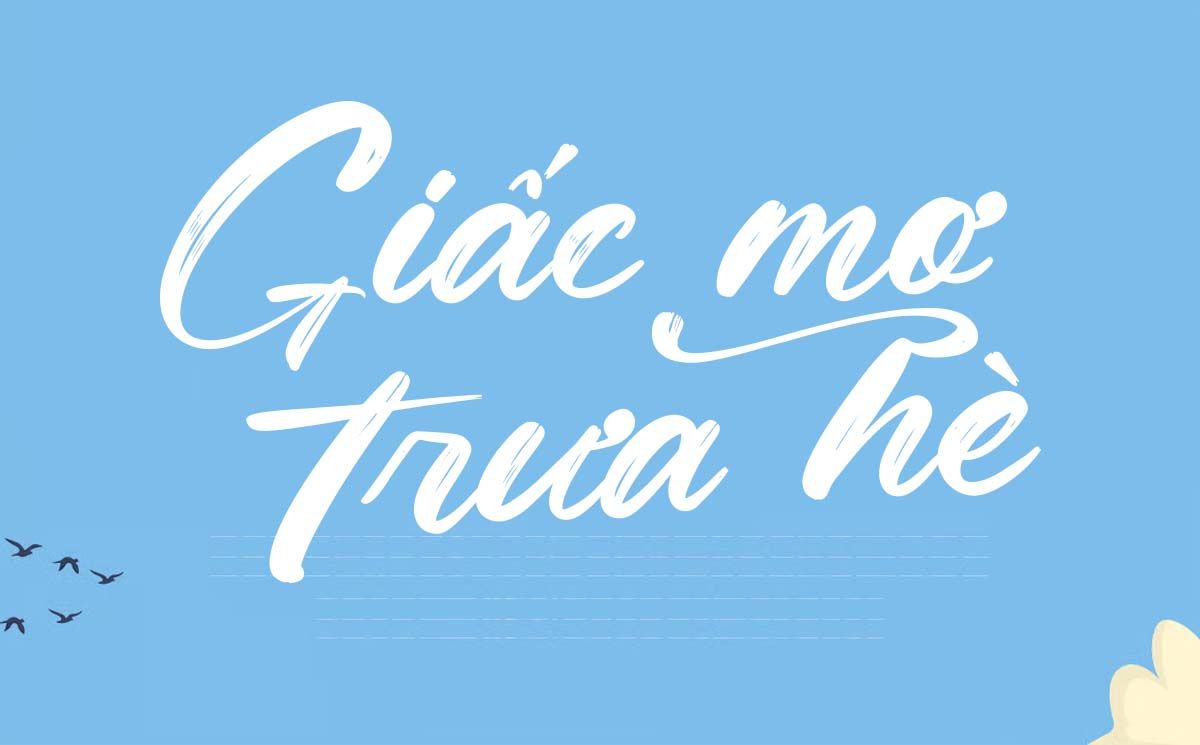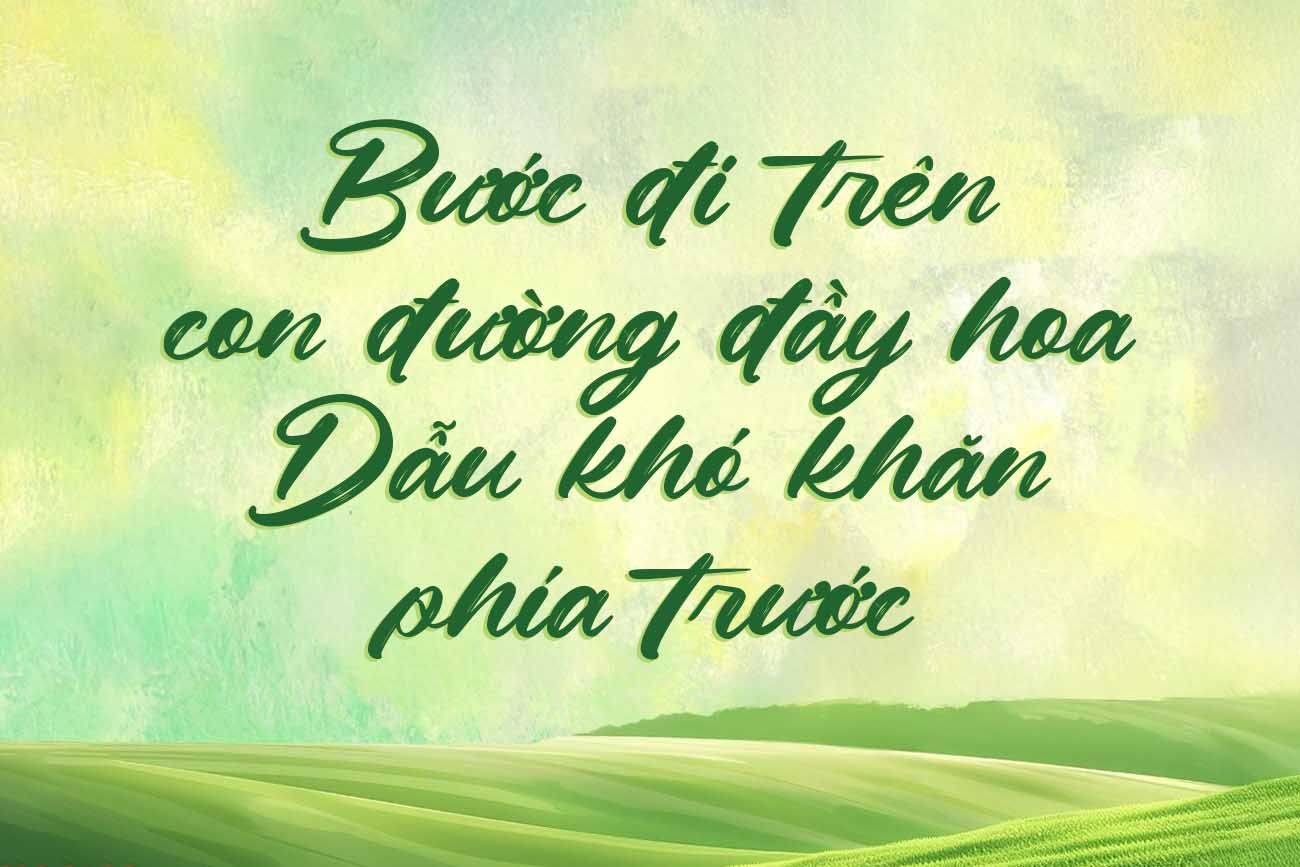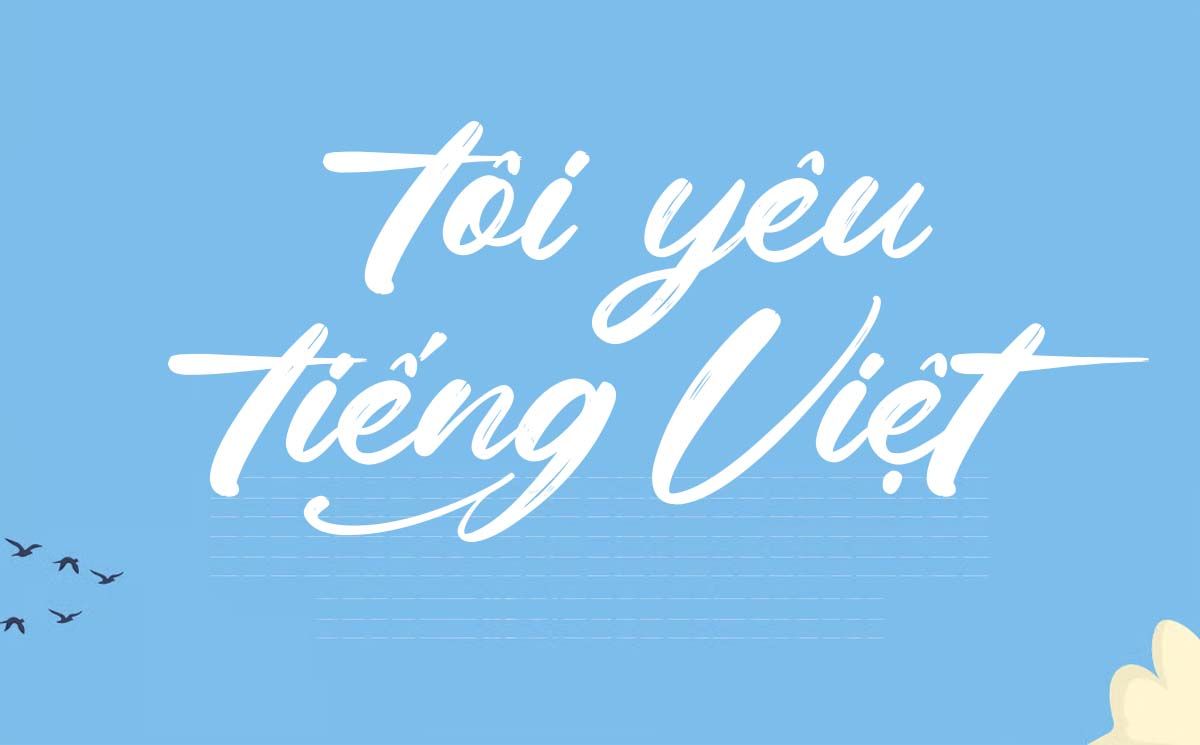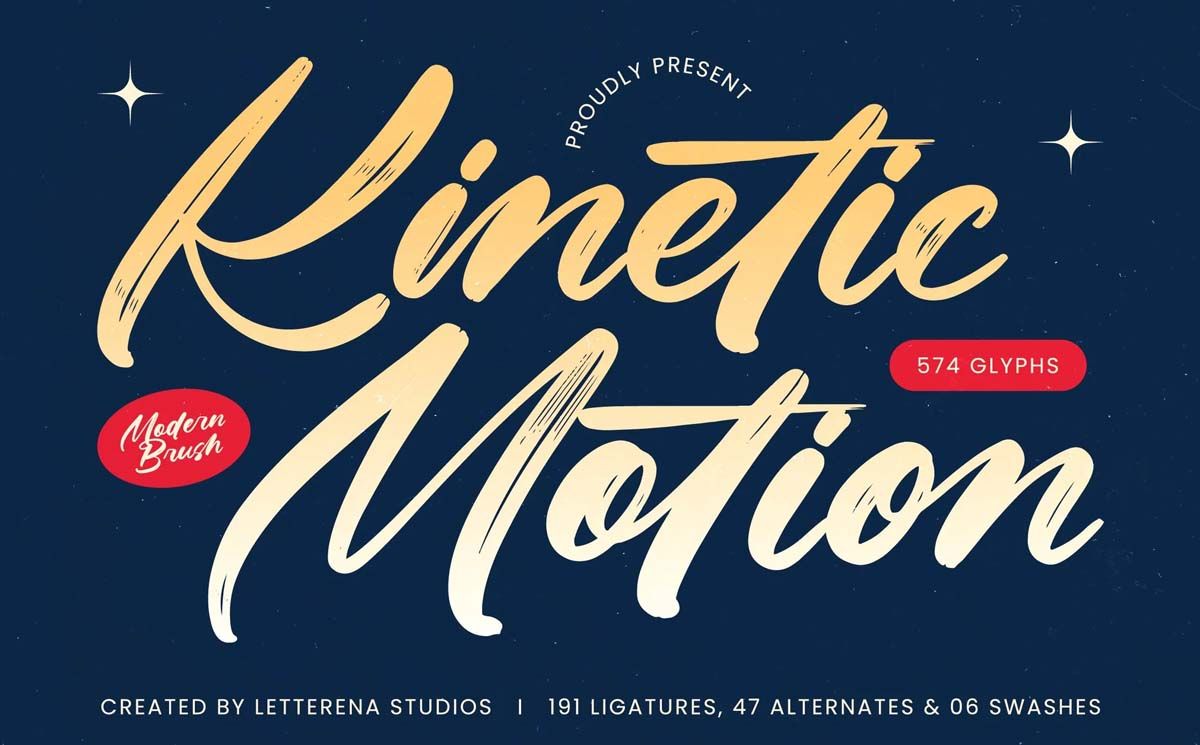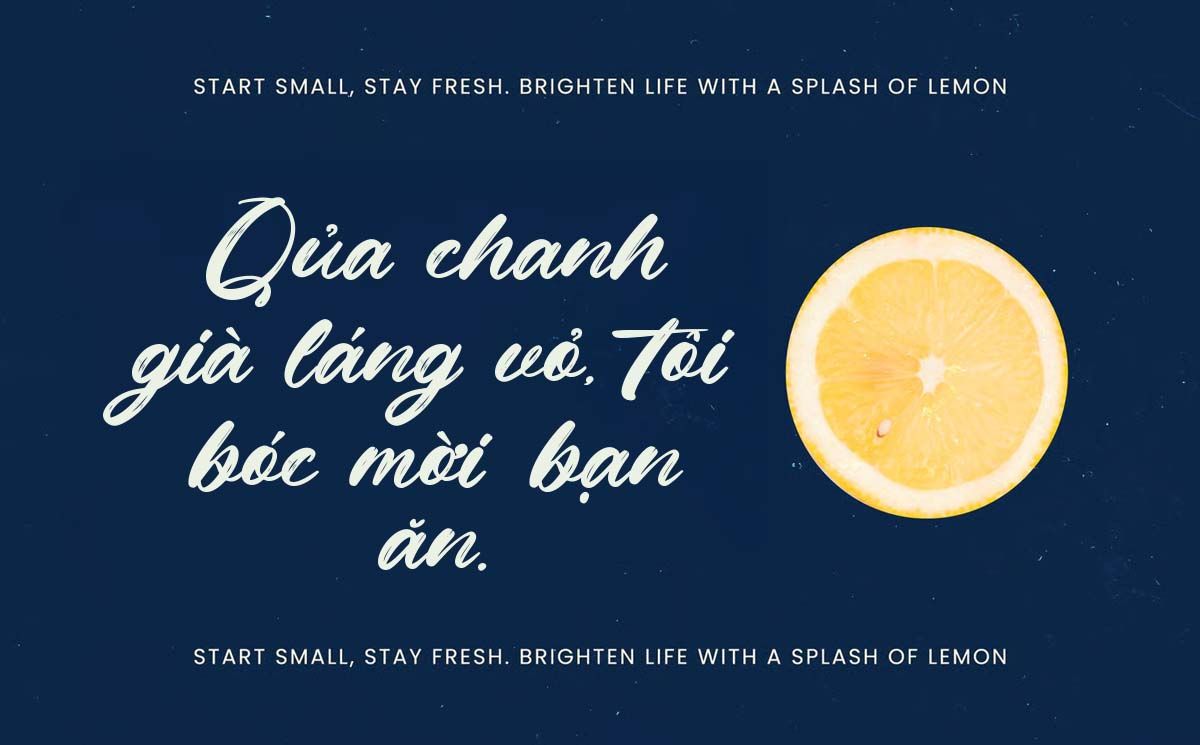
![[Tải Xuống] Font Brush Kinetic Motion Việt Hóa – Phong Cách Brush Cực Chất, Năng Lượng Và Táo Bạo](https://cdn.s99.vn/z0/833b639681e4a01026c63ca058c85869/p/iie0di0erz/76bec9d6293337f0099bcdbec1d727fa.jpeg)
Chào bạn, mình là Phạm Sơn – người Việt hóa bộ font chữ Kinetic Motion. Trong bài viết này, mình sẽ chia sẻ chi tiết về bộ font này: từ nguồn gốc, phong cách thiết kế, đến các ứng dụng thực tế mà bạn có thể khai thác tối đa sức mạnh của nó.
Nếu bạn đang tìm một font brush đậm cá tính, mang đậm tinh thần chuyển động, hành động, bùng nổ, thì đây chính là sự lựa chọn lý tưởng.
Kinetic Motion là một kiểu chữ viết tay theo phong cách brush script, được thiết kế bởi Maulana Creative – một studio thiết kế chuyên về font chữ hiện đại và năng động. Font mang trong mình tinh thần "kinetic" – tức là năng lượng chuyển động, kết hợp với những nét vẽ bằng cọ dày, loang, gãy gọn, tạo cảm giác như một cú vung tay mạnh mẽ, đầy tốc độ và quyết đoán.
Mình đã Việt hóa đầy đủ bộ font này, bao gồm tất cả ký tự tiếng Việt có dấu, để bạn có thể sử dụng trọn vẹn trong mọi dự án thiết kế.
Ngay từ khi nhìn thấy bản gốc, mình đã bị ấn tượng mạnh bởi cảm giác chuyển động mà font tạo ra. Những đường nét như được vẽ một cách tự nhiên bằng cọ bản, có vệt sơn loang lổ, nét đậm nét mảnh đan xen đầy ngẫu hứng – nhưng không hề thiếu kiểm soát.
Kinetic Motion không đơn giản là một font chữ, mà là một tuyên ngôn thị giác: mạnh mẽ, phá cách, phóng khoáng, như chính cái tên của nó.
▪️ Tên font: Kinetic Motion
▪️ Thiết kế bởi: Maulana Creative
▪️ Việt hóa bởi: Phạm Sơn (S99.vn)
▪️ Số kiểu chữ: 2 (Regular & Italic)
▪️ Hỗ trợ: Unicode đầy đủ, dấu tiếng Việt, ký tự đặc biệt
Mình đã tinh chỉnh lại dấu tiếng Việt sao cho cân đối với từng chữ cái, giữ nguyên tinh thần brush mạnh mẽ nhưng vẫn đảm bảo dễ đọc – đặc biệt là khi dùng ở kích thước lớn như tiêu đề.
Kinetic Motion phù hợp với những thiết kế cần tạo ấn tượng thị giác mạnh. Phong cách của font này thiên về:
▪️ Street style / Urban typography
▪️Poster phim hành động, thể thao, eSports
▪️Typography nghệ thuật
▪️Bìa sách, tiêu đề tạp chí
▪️Thiết kế social media năng động
Dù bạn đang làm một poster sự kiện âm nhạc, một video intro thể thao, hay chỉ đơn giản là muốn tạo ra dòng chữ có cá tính riêng, font này đều mang lại hiệu quả vượt mong đợi.
Mỗi font mình chọn để Việt hóa đều có một lý do rất rõ ràng. Với Kinetic Motion, mình chọn vì:
▪️ Nó có năng lượng mà không phải font brush nào cũng có
▪️ Nét cọ mạnh, không bị mềm yếu, cực hợp với tinh thần hành động – tốc độ – cá tính
▪️ Chữ viết tay nhưng rõ ràng, dễ đọc, không bị rối
▪️ Bộ ký tự gốc được làm rất kỹ – không bị lặp lại nhàm chán
Việt hóa bộ này khá vất vả vì phải tạo lại dấu tiếng Việt thủ công, canh chỉnh tỉ lệ và độ nghiêng để không phá vỡ bố cục gốc. Nhưng khi hoàn tất, mình rất hài lòng – vì nó hoạt động cực tốt trong thiết kế tiêu đề, logo, banner cỡ lớn.
Để khai thác tối đa sức mạnh của font Kinetic Motion, bạn nên sử dụng ở kích thước lớn như tiêu đề, khẩu hiệu hoặc tagline thay vì body text, nhằm đảm bảo tính rõ ràng và ấn tượng. Kết hợp font với các background có texture như giấy nhám, bê tông hoặc sơn nước sẽ giúp tăng hiệu ứng thủ công và cảm giác chân thực. Ngoài ra, phối hợp hai kiểu Regular và Italic có thể tạo ra chuyển động mượt mà hơn trong thiết kế, đặc biệt khi thêm một chút bóng đổ nhẹ hoặc hiệu ứng vệt sơn, giúp tăng chiều sâu và thu hút thị giác mạnh mẽ hơn.
Với mình, Kinetic Motion không chỉ là một font chữ – mà giống như một nguồn năng lượng đầy cảm hứng. Mỗi nét cọ vung lên là một lời khẳng định: mạnh mẽ, khác biệt và luôn chuyển động không ngừng. Nếu bạn đang cần một kiểu chữ cá tính để làm nổi bật dự án của mình, mình tin rằng Kinetic Motion Việt hóa sẽ là một người đồng hành tuyệt vời, giúp bạn truyền tải trọn vẹn cảm xúc và thông điệp thiết kế. Chúc bạn sáng tạo thật nhiều điều thú vị nhé!